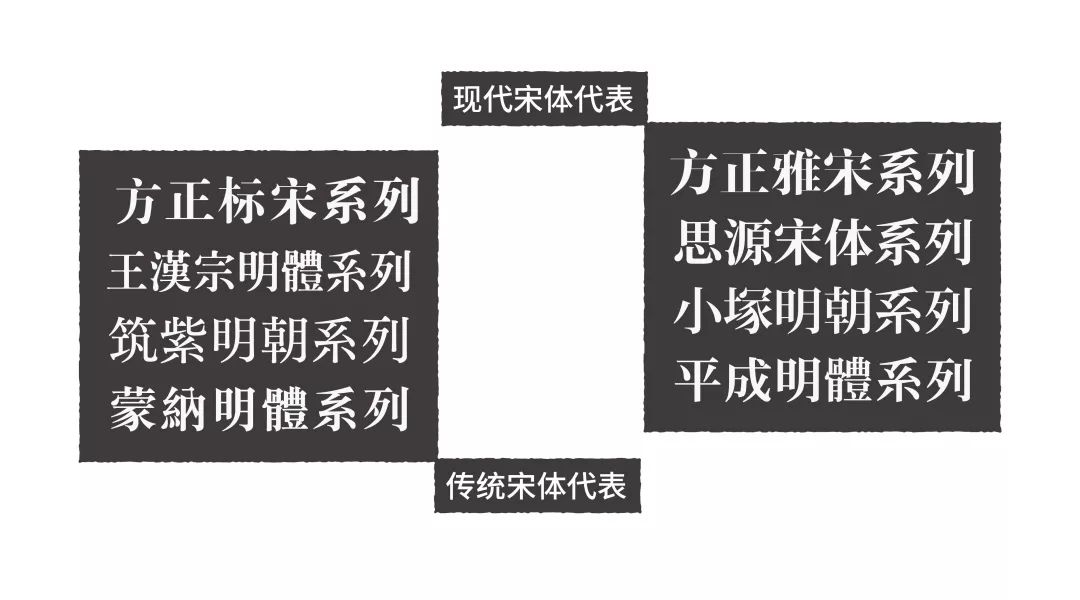
排版优劣的三大要素,墙裂干货!
一、 格式塔原理及其版面中的应用
相信各位都听说过格式塔心理学。“格式塔”源自德语“Gestalt”,意即“整体”、“完形”。
简言之格式塔心理学是对人类视觉工作原理研究。此项研究提出人类的视觉是一个整体,眼睛所看到的事物都是经过大脑整体化处理,所以我们是以整体形式感知事物而不是个体元素。
其中最重要的格式塔原理有着几个:接近性原理;相似性原理;连续性原理;封闭性原理;对称性原理;主体/背景原理。 在此篇文章中我们重点介绍前三个,而这三个也是在版面中运用最广泛最基础的。
1.1 接近与信息关联性
何为接近原则?即我们视觉会把彼此接近的元素看成一个整体。所以在排版的时候我们可以将相关联的元素彼此接近,不相关的元素彼此远离,以此来区分不同的信息集。
建立不同组合的方式有很多种,但是以接近性原则最为基础和重要。即便每个元素的颜色形状不同,但只要彼此接近,也能够在视觉上形成一组。
例如:联合利华LOGO的诸多元素因为彼此接近,所以我们很轻易的能够辨认出轮廓“U”。
那么接近原则在版面中是如何运用的呢?其实就是将相关联的信息彼此靠近,不相关的信息彼此远离的过程。
在这个名人名言的案例中,标题与内容之间的距离完全相等,我们很大程度上就会产生哪段标题对应哪段文字的疑惑。如果我们将接近性原则处理好之后会发生什么?
当我们把相对应的名人名言互相贴近,不相关的互相远离后,其阅读障碍就不存在了,谁说了那句话一目了然。
接近性原则不但可以处理标题与文字,还可以处理各种各样的元素。
在此案例中,图片与文字距离过远,缺乏联系感。而图片之间又过近,组合不分明。接近性没有做好,所以造成了画面整体偏散的问题。
当我们用接近性原则将相关联的图文信息组合在一块后,版面更易阅读,哪个人物对应哪个名字也不会出错了。
我们再来看一下这组信息,需要用以下信息做一个中英文结合的名片。首先要做的还是把接近性原则处理好,把姓名职位、英文名、联系方式、地址等通过接近性原则划分为不同的组合。
右边经过接近性原则处理后的更易阅读,哪块信息说了什么也十分明显,剩下的我们只需要把划分好的组合选择合适的字体,并排列到名片的版面中。
(Ps:关于如何选字体下文会讲到)
利用好接近性原则我们可以不断尝试已经分好组的元素在版面中的位置,在确保每组距离的同时保证版面的平衡性即可。
利用接近性原则可以不断的去调整位置形成新的版面。
以上都是以接近性原则为基础延伸出的不同布局的名片。
1.2 相似与版面统一性
接近性原则强调的是位置对我们视觉的影响,而相似性原则强调视觉元素的内容对视觉的影响,如颜色、形状、大小、方向等等。如果其他因素一样,只有这些内容不同,那么我们的视觉会把相似的内容看成一个整体。
在同一组图形中,颜色或者形状相似的元素会形成一个视觉单元。
同样的原理,在一组图形中大小或方向相似的元素也会形成一个视觉单元。
相似性原理在版面上是如何去运用的?
首先利用相似性原理可以把不和谐的元素和谐化。
三张图片的色调不同,强行组合在版面中并不和谐。
将色调处理成统一版面也会更加和谐。
不同的数字表现方式使版面凌乱不堪。
将数字的特征相似化后整体的风格更统一,版面也没了凌乱的感觉。
相似性原理除了可以和谐的处理版面之外还可以着重突出重点的元素。
我们只需要将想要突出的元素去掉相似特征就可以了,使之异于其他相似的元素。
此例中用不同的色彩使已完成、待进行、正在处理的流程区分开来。而“已完成”的步骤其颜色则是一样的;“未完成”之间的色彩也一致,这正是相似原则的突出运用。
1.3 连续性原则与视觉逻辑
我们的视觉更容易感知到连续的事物,使之成为一个整体。
以上图而言,虽然全部是虚线的点,但我们依然可以辨认出他们的几何形状。
有很多LOGO造型也是运用了连续性的,比如IBM。
分隔开的图片我们依然能够识别出内容,也说明了视觉是连续的。
连续性在排版设计中一般用于解决元素散乱、视觉逻辑的问题。
为解决这个问题,我们可以加入其它元素,建立连续性。
通过线条的穿插表现,我们的视觉得到了很好的引导,解决了不知按什么顺序阅读的问题。另外线条使四个点连成了一个整体,点与点之间具备了连续性,散乱的问题也得到了很好的解决。
线条的走向也会对我们的阅读顺序产生重大的影响。
这里考一下大家,如何利用连续性原则将上图比较散的年份和日期建立联系感?要求不能改变两者的距离。
好了,时间结束啦,我们看一看答案吧。
另外我们的视觉流向也会被画面中的目光朝向所影响。
我们现在要将BIG Cat 放到画面里面,放到什么位置最能让别人注意到?
放到这里虽然感觉也没问题,但是如果字再小一点,图片颜色再深一点就非常容易让观者遗漏此信息。
将“BIG Cat”放到猫咪目光的延伸线上则会非常容易使人注意到。
二、 素材的精致程度
素材的精致程度对版面的优劣也有非常大的影响,素材的精致程度主要体现在三个方面,分别是清晰度、契合度和表现力。
2.1 清晰度
清晰度相信不用多说了吧,清晰度的优劣直接会影响我们作品的品质。如下图中这类素材清晰度不够,排版就会毁于素材。调换成足够清晰度的素材,画面也会精致很多。
2.2 契合度
契合度就是素材与主题的关联程度,如果一个表现体育的主题你去找一张美食的图片,那么毫无关联程度,必然是错的。
上图左侧的案例文字是狗,但素材图却是个豹子,于是就成了契合度不够的典型。
同样是书法培训的海报,左侧的用到太多不相关的元素,庙宇、竹子、山川等等,与主题的契合度不够。而右侧的案例仅仅只用了书法笔触的素材,但契合度和表现力却比左侧好很多。另外右侧文字的编排在接近性、连续性上也比左侧案例好很多。
3.3 表现力
表现力有多重形式,如创意性、光影出色、层次感强等等。
比如我们找一个舞者的素材,下图左侧这种就属于表现力不够的。
左侧的素材常见,造型、创意以及美感都差强人意,缺乏感染力自然表现力就不够。相比较右侧素材的光影以及美感非常好,表现力就会强很多。
上图两案例也属于表现力非常好的素材,我们在做排版时,如果要用素材就要用表现力过关的素材,这样作品才会更有美观与设计感。
三、 字型选择的重要性
字型在我们设计中是非常重要的,甚至可以上升到设计之魂的高度。字型选择是否正确对版面的影响是决定性的。
再讲字型之前我们先看一个案例
这个生命科学的海报看上去怪怪的,究竟怪在哪里呢?实际上是字体应用不得当的问题。案列中用的是衬线体与宋体,而这两个都是传统型字体,表达不出生命科学所拥有的严谨感与现代医学的科技感。
当我们将字体换成无衬线体与黑体后是不是就顺眼多了。无衬线体更加现代,与要表达的主题气质契合。
由此可见字型选不对,就很容易毁掉你的作品。要选对字型首先要对字体的气质有一定的了解,接下来重点介绍衬线体、无衬线体、黑体、宋体所具备的不同的气质。
3.1 衬线体与宋体
衬线体,即有衬线装饰特征的字体;宋体,即笔画有粗细变化,并且转折处有三角装饰特征的字体;衬线体与宋体一般都具有传统的气质,能够表现一定的文化感、历史感,并且具有强烈的人文主义感。
衬线体还可详细分为偏传统和偏现代的类型,主要是看他们的横竖笔画的粗细对比度与简洁程度区分。
左侧传统型衬线体粗细对比相差比较小,衬线也比较圆润复杂,衬线连接处呈圆角;右侧现代型衬线体粗细对比相差非常大,衬线连接处呈直角,简单直接,。
偏传统衬线体的代表有Garamond、Caslon等。他们的传统气质非常强烈,适合传达传统、文艺、人文的气质与故事感。
说完偏传统的咱们再来说一下偏现代的。
偏现代衬线体的代表有Didot、Bodoni、Walbaum等。他们在保留衬线的同时又有很强的现代感,粗细对比也比较大,能够传达出优雅、女性、高端、时尚的气质,因此很多时尚杂志、女性产品选择此类型的字体。
既然衬线体分为传统衬线与现代衬线,那么宋体也是一样。按照宋体装饰三角的复杂程度也可分为传统宋体与现代宋体。
常用的传统宋体有方正标宋、书宋、报宋、筑紫明朝、王汉宗明体等;而常用的现代宋体有方正雅宋系列、思源宋体、小塚明朝等。
传统宋体与现代宋体所传达的气质也有差别。传统的宋体更能够表现出文艺、故事、人文的感觉;而现代宋体则偏向传递女性优雅、时尚的感觉。
介绍完宋体与衬线体的相同与不同后我们再来说一下他们之间应该如何混合搭配。
搭配原则其实不难,总结就是一句话
以这个搭配原则我们看一下下面这个案例。
第一组搭配为方正风雅宋与其自带的英文,显然是不匹配的;第二组为方正风雅宋+Garamond,现代宋体搭配传统衬线体,显得也不伦不类,不和谐;第三组为现代宋体搭配现代衬线Didot,所以非常和谐。
这一组也是一样,只有第三组传统宋体+传统衬线体最为和谐。尽管第一组自带的英文也可勉强划分到传统衬线里面,但他的笔画特征与中外完全不同,因此也非常难匹配。
所以搭配的时候不仅要气质相匹配,其笔画特征也应该是相似的。
3.2 无衬线体与黑体
无衬线体,即没有衬线修饰的字体。黑体也是没有三角形装饰特征的字体。相较于衬线体与宋体而言,其更为简约、现代,能够表达理性、利落的特质。
无衬线体根据其字母的结构关系可以分为常规型、人文型、几何型三类。
其中常规型无衬线体是最常见最普通的,可以说是最没个性的;人文型无衬线体的笔画并不是等宽的,而是有过渡过变化,S、C等字母的切口也是宽的,给人的感觉很秀丽、优雅,同时又具有一点文艺气质;几何型无衬线体更像是用几何形状切出来的,给人的感觉很简约、时尚、现代。
常见的常规型无衬线体有Helvetica、Univers、DIN等,他们给人的感觉是现代、理性、严谨的,同时也是最没个性的。
因为其没有特别的个性,所以字体的包容性非常广,有话云:当你不知道用什么字体时,就用Helvetica。由此可见其用途广泛程度。
人文型无衬线体的代表为Gill Sans、Optima、Stone Sans等,人文型无衬线体给人感觉是理性与感性并存,是很有温度的一类字体。他们也能传达优雅、秀丽、人文的气质。
几何型无衬线体的代表有Ftura、Avalon、Avant Garded等,这种字体有强烈的几何感,显得很现代、高端。
相对于无衬线体,黑体的分类就比较简单了,按照有无喇叭口的原则只将其分为常规型黑体与人文型黑体。无喇叭口的黑体为常规型,有喇叭口的为人文型。
常见的常规型黑体有思源黑体、微软雅黑、汉仪旗黑、方正兰亭黑等;常见的人文型黑体有默认黑体和冬青黑体。
黑体与无衬线体的搭配比衬线体和宋体要简单,只需要选择精致的字体,并统一好字重和笔画形式便可。
四、 案例演示
此部分我们用“东方艺蕴”的海报来作为案例,来看看如何运用以上的知识点运用到版面设计中去。
首先我们看一下同学的原作极其所存在的问题
第一点是所用的素材不够精致,不管是层次感还是表现力都非常的差。
第二点是字形选择上的错误,中文与英文的搭配也并不合理。
第三点是接近性原则没有处理好,版面的层级关系也没有划分好,所以显得很碎且杂乱无章。
知道问题后我们来逐一解决就可以了。首先来看第一点,素材的精致程度。
随着此素材层次感和表现力都不太好,但也并不是完全没救,我们只需要在PS里处理一番,提高其层次感和表现力。
处理后素材的层次感通过浮雕效果表现了出来,增添一些东方韵味。对其色阶、对比度的调整更使其表现力增加了几分。
虽然调整好了,但素材的负空间比较多,比较零碎,所以我们可以为他加入一个底,最好贴合着形体来,我这里加了一个渐变的圆形,形式贴近中国特色民族传统工艺之一的刺绣,与活动主题契合不少。
现在主体非常饱满了,但后面的圆形缺乏层次感,为了解决这个问题我们可以去找一些纹理的素材叠加上去。
当我们把纹理叠加上去后,其视觉表现更丰富了,层次感也比之前强很多,至此素材精致度的问题已经得到了解决。
Ok,我们可以将处理好的素材置于版面之中作为主体,如下。
现在主体在版面中的大小已经调整的比较合适了,剩下的我们只需要在主体以外的区域编排上文字信息便可。在此图中能够放置文字信息的区域也就只有上下两部分,如下。
了解文字编排的位置之后我们需要解决第二个问题,也就是中西文字体搭配的问题。在做之前我们首先应思考其表达的主题是什么,是传统的感觉还是现代的感觉、该用黑体还是宋体?
东方艺蕴明显是东方的艺术展,非常有文化感与艺术性,所以黑体与无衬线体肯定是不合适的,我们应该选择能够表现文化属性的宋体类字形。
在宋体字形里面我们也要避开具有时尚、现代气质的,而要选用传统的、有文化性的字体——传统宋体。
确定好中文宋体的类型之后我们还要去确定英文字形,根据我们上文所说的传统配传统的法则,上面三个搭配中只有王汉宗明体与Garamond的搭配最为合适。
字形都确定好后便可以进入排列文字信息的环节。
首先把主标题放上去,但主标题字与字直接空隙太大,有些散,怎么解决这个问题呢?
根据我们上文所说,在字与字之间加入连接性的符号就可以了,这样建立了连续性,使其成为了一个视觉组合。
其他的信息也按照接近性的原则排列上去,注意相关联的信息互相接近;不相关的信息互相远离。
现在版面的结构已经成型了,剩下时间日期这里显得有些散。
同样我们也为其加入连接性的符号组织到一个视觉单元里去,那么其整体的效果就会好不少。
深灰色背景太单调了,所以我们可以另找一个密一点的纹理素材叠加上去。
叠加上去之后我们看一下其局部效果,
再看一下整体的效果和运用效果。
至此,这个案例也就完成了。
总结:
1. 要做好版面一定要去选择精致的素材作为主体,素材的精致与否很大程度上能够决定版面的优劣。素材不够精致,可以二次处理,二次处理也抢救不了的素材就赶紧换吧。
2. 素材的精致程度是其一,有了精致的素材还需要通过格式塔原理将信息的层级拉开。用接近性原则处理好信息的贴近与远离;用相似性原则平衡版面不同元素间的视觉和谐度,也可用此原则强调需要突出的信息;用连续性原则使散乱的信息形成整体,建立视觉逻辑。
3. 字体选择和中英文搭配要契合项目的气质,并且笔画特征相似。一定不要随意的去选择字体,每种字形都有其特定的气质,只有选择正确的字形,版面所传达的主题气质才会更加明确。